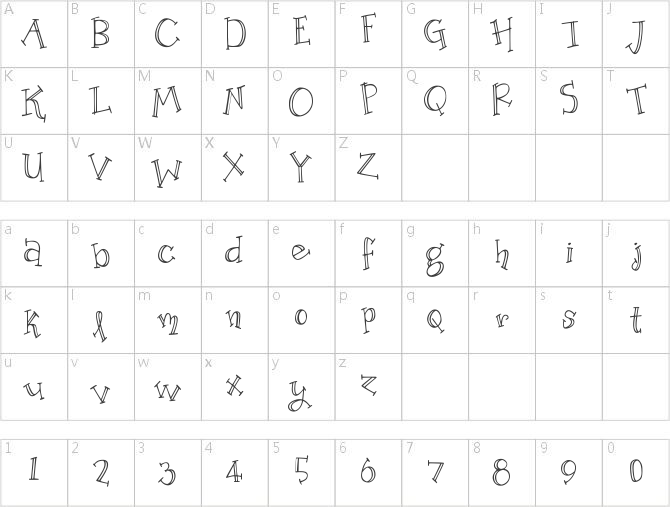
字體名稱: Organic
Organic-Fridays-Lined
Organic-Fridays-Lined介紹
Organic-Fridays-Lined字體字庫是一款讓人賞心悅目、百看不厭的英文字體,適合各類廣告和產(chǎn)品包裝設計應用,字體大小0.12MB,格式為ttf字體,上傳用戶是 造物設計師,作者/版權方為未知